A kalligráfiát nemcsak azért szeretem, mert teljesen kikapcsol, hanem azért is, mert remek személyre szabott ajándékot lehet készíteni. Ez például az egyik kedves ismerősöm esküvőjére készült.
Mi is kell hozzá?
Először is természetesen egy bögre. A kedvenc lelőhelyem az IKEA, ott van a legtöbb sima bögre, ami díszítésre termett, és elég nagy a választék is formában és színben.
Kell hozzá egy filc, szokásos kedvencemet használom, a Poscat, a 3M-est, de használhatsz másik tollat is, ami porcelánra ír. A skicchez használhatsz fehér akvarell ceruzát, én már nem szoktam, mert az az érzésem, hogy emiatt kevésbé tapad jól a tinta.
A tuti eszköz pedig egy babzsák párna, mindjárt megmutatom, hogy miért.
A díszítés
Helyezd rá a párnára a bögrét és a kezednek is találd meg a megfelelő pozíciót. Fontos, hogy a könyököd felfeküdjön a felületre, amin írsz, így stabilan fogsz tudni írni. Ez a titok, hogy minden domború felületre tudjál írni, mert így a bögre, pohár vagy bármi stabilan van, és nem a kezedben tartva kell írni.
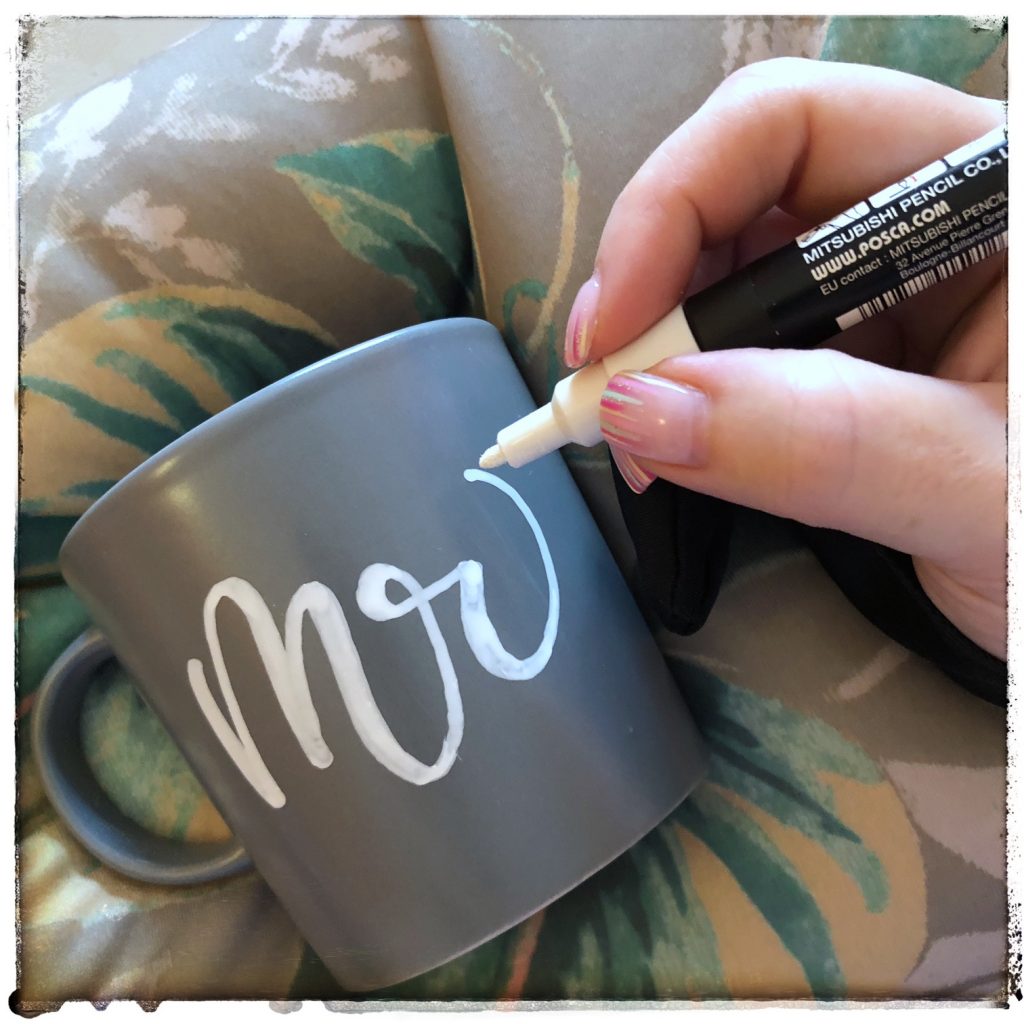
Az eszközöknél elfelejtettem említeni, hogy érdemes alkoholt is használni. Na nem meginni 😉, hanem először a felületet kell zsírtalanítani, vagy ha elrontod, ezt tudod használni a nyomtalan törléshez.
Szóval, ha elhelyezkedtél jöhet az írás, én itt hamis kalligráfiát használtam, mert a Posca ecsetfilcét nem szeretem, nagyon halvány. Sokszor emlegetem a Posca filceket, de még nem említettem, hogyan kell használni. Fontos, hogy alaposan felrázd használat előtt. A tinta akkor áztatja át a hegyet, ha finoman benyomod azt. Ezt az első használat előtt viszonylag sokszor kell megtenni, mármint a nyomkodást. Ha már többször használtad, akkor elég egyszer-kétszer mielőtt írsz vele. Elvileg a hegye cserélhető, ha túlságosan elhasználnád, én még nem próbáltam, nem volt rá szükségem
Vissza az íráshoz, itt arra kell figyelni, hogy ne száradjon meg teljesen a tinta, mert különben nem tudod a vastagítást szépen megtenni. Ha újra át akarod írni, nagyon óvatosan tedd meg, mert felkarcolhatod a már felírt szöveget, és nem lesz szép egyenletes. Mielőtt még egyszer átmész érdemes kicsit jobban átnevesítened a tintával a hegyet. Természetesen mivel esküvői ajándék a szívecske sem maradhatott el, ehhez az új glitteres Posca filcet használtam, van egy kis metálos fénye.
Ha elkészültél, akkor hagyd megszáradni. Érdemes ezt vízszintesen megtenni, hogy ne folyjon el a tinta. Száradás után mehet a sütőbe, 45 perc és 160 fok. Ezzel fixálod az elkészült művet, így már vízálló. Azért nem ajánlom, hogy szivaccsal neki ess, de egy lightos mosogatás belefér.
Ennyi már készen is vagy, ugye milyen egyszerű?
A kis ajándékcsomagból nem maradhatott ki a tábla sem, ezt azonban már az előző bejegyzésben bemutattam, így most nem mennék bele, ugyanazt a technikát alkalmaztam, csak most nem pácoltam a fát, tetszett a natúr színe és textúrája.